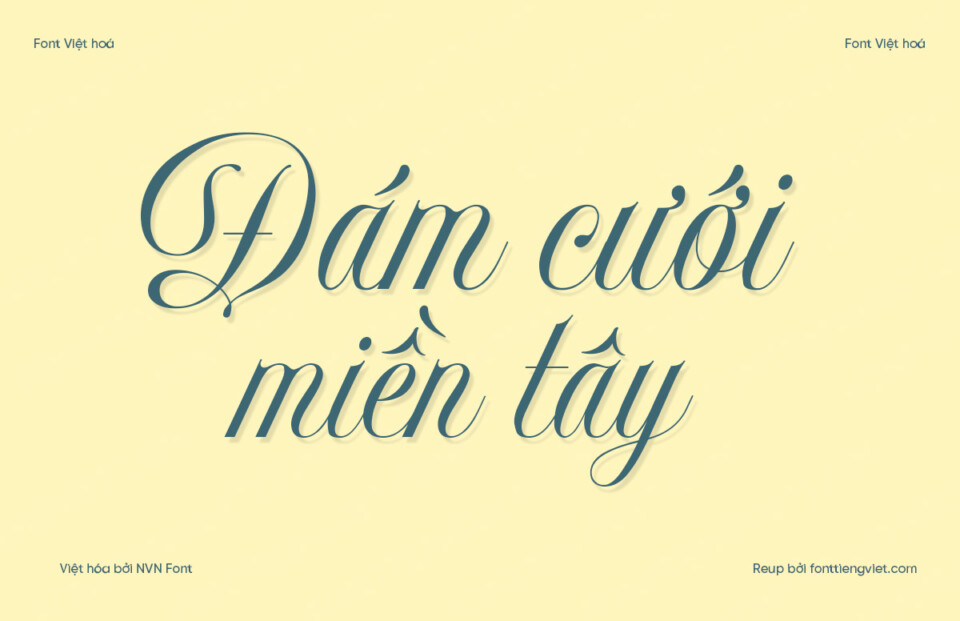
Font Việt hóa NVN Delirian Script
Font Việt hóa NVN Delirian Script là font chữ viết tay dạng script mềm mại, bay bổng, phù hợp thiết kế thiệp cưới, logo, tiêu đề poster và nội dung trang trí. Bộ font hỗ trợ tiếng Việt đầy đủ dấu, dễ cài đặt và dùng trên nhiều phần mềm thiết kế phổ biến.
Font Việt hóa NVN Delirian Script – Script viết tay mềm mại, sang trọng
Font Việt hóa NVN Delirian Script là lựa chọn lý tưởng cho những thiết kế cần cảm giác tinh tế, lãng mạn và giàu tính cá nhân. Với phong cách script viết tay mềm mại, các nét chữ uốn lượn tự nhiên giúp bố cục trở nên nổi bật mà vẫn giữ được sự sang trọng.
Điểm nổi bật của NVN Delirian Script
• Hỗ trợ tiếng Việt đầy đủ dấu: dùng tốt cho tiêu đề, slogan, câu trích dẫn.
• Phong cách chữ ký/calligraphy: phù hợp logo cá nhân, branding, thiệp cưới.
• Dễ kết hợp font: đi cùng sans-serif hoặc serif để cân bằng bố cục.
• Ứng dụng đa dạng: poster, banner, social post, menu, bao bì, in ấn.
Gợi ý cách dùng để thiết kế đẹp hơn
Khi dùng Delirian Script Việt hóa, bạn nên ưu tiên cho tiêu đề hoặc các cụm từ nhấn mạnh. Tránh dùng cho đoạn văn dài để đảm bảo khả năng đọc. Có thể tăng tracking nhẹ, chỉnh line-height hợp lý và phối màu tương phản để chữ “bay” hơn trên nền.